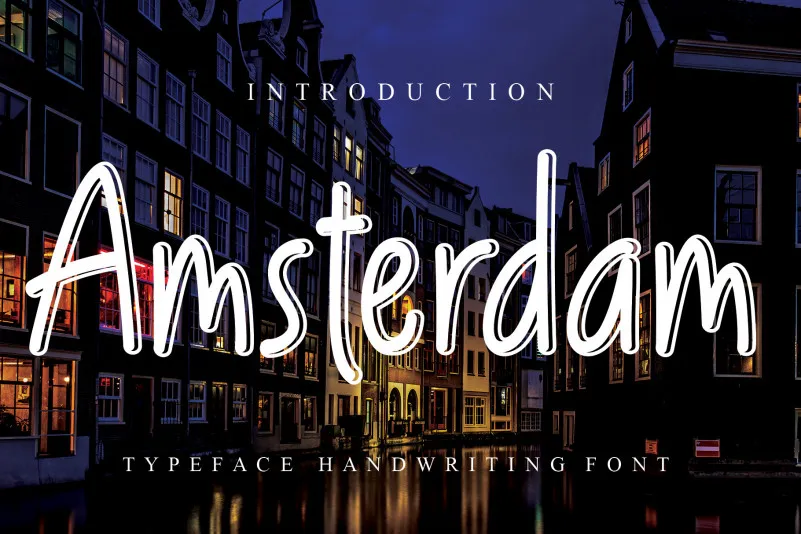
Amsterdam Display Font – Download Grátis
A Amsterdam Display Font é uma fonte escrita à mão casual perfeita para criar designs únicos e excepcionais. Seus traços suaves e agradáveis ao olho capturam um toque de naturalidade, tornando-a ideal para aplicar em design gráfico que valoriza essa qualidade única. Esta fonte é especialmente conveniente para designers buscando adicionar uma nota pessoal ou original aos seus projetos digitais, seja em logotipos, banners ou mensagens digitais. Ideal tanto para quem busca um visual elegante quanto para aqueles que desejam dar um toque autêntico e descontraído ao seu trabalho de design. Com o Amsterdam Display Font da andikastudio, você pode explorar diferentes maneiras de incorporar esse estilo particular em seus projetos, permitindo que as suas criações sejam ainda mais vívidas e memoráveis.